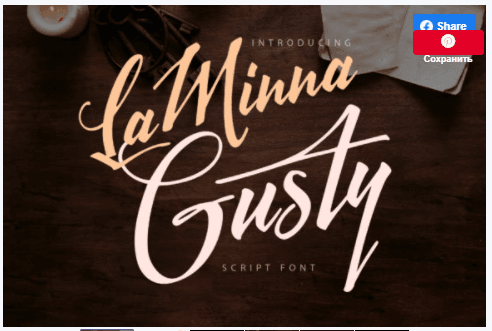
LaMinna Gusty Font
LaMinna Gusty - это стильный и изысканный рукописный шрифт, который источает элегантность и класс. Этот шрифт был специально разработан для тех, кому нужен красивый и освежающий вид своего дизайна.